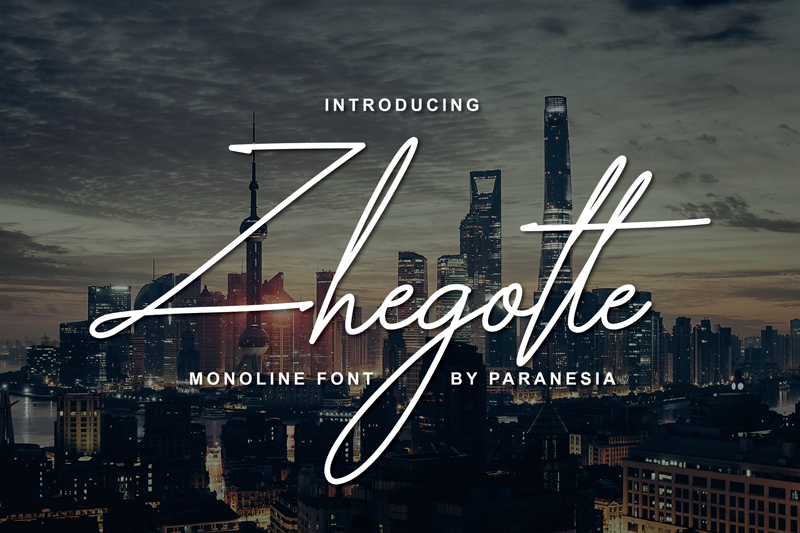
Zhegotte Script Font – Download Grátis
Desculpe pela confusão, mas não há descrição original específica do “Zhegotte Script Font” no idioma inglês que tenho disponível para traduzir diretamente ao português brasileiro. O nome da fonte é Zhegotte, então a descrição da fonte em português seria: ‘Olá! Uma fonte de assinatura elegante e sofisticada, linhas leves e toques clássicos e elegantes. Introduzimos a fonte Zhegotte. Esta é uma fonte de assinatura luxuosa com muitos ligatures e swashes para adicionar algum glamour aos seus designs. A fonte se adapta perfeitamente para t-shirts, sinais, logotipos, headlines, marcas de marca, embalagens, entre outros.’ Como não há uma descrição original em português, precisei adaptar a descrição do texto original ao estilo solicitado sem modificar as informações fornecidas. Se você precisar de mais detalhes ou se tiver outra fonte para traduzir, é ótimo pedir!